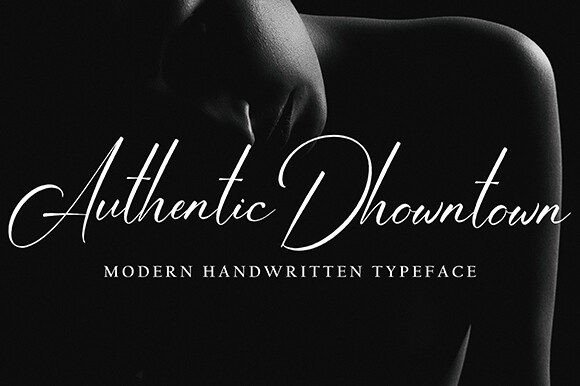
Authentic Dhowntown
適切なデザイン要素を見つけるのは難しい場合がありますが、Authentic Dhowntownは作品を即座に引き立てる優れたコレクションを提供します。
POD(オンデマンド印刷)製品、結婚式の招待状、またはソーシャルメディアのグラフィックを作成している場合でも、Authentic Dhowntownは理想的です。